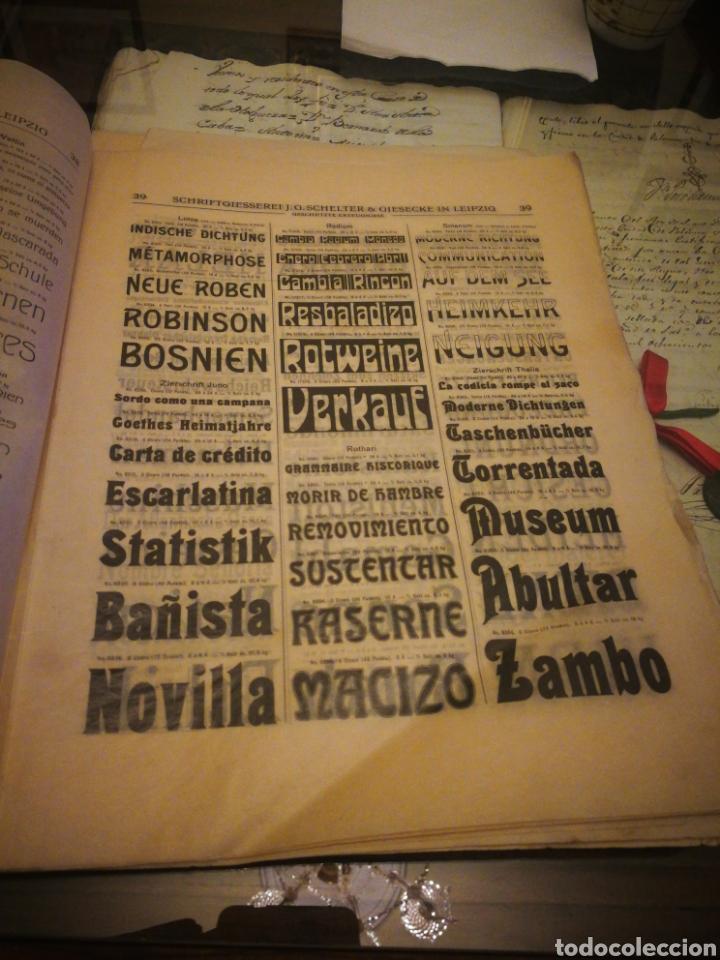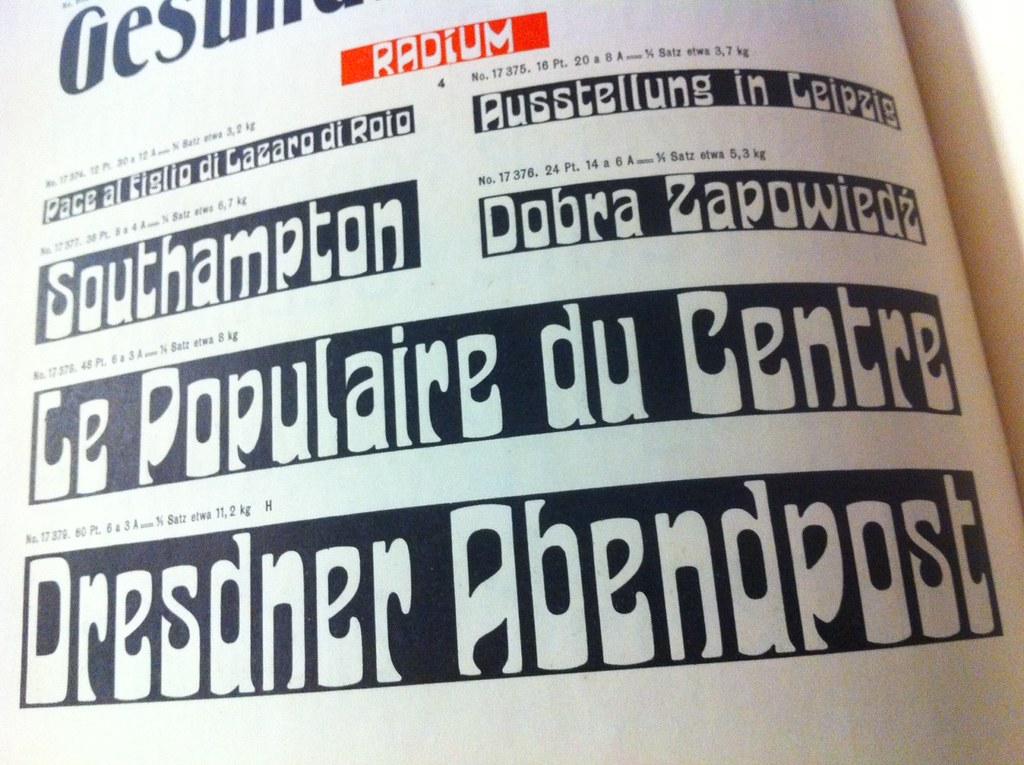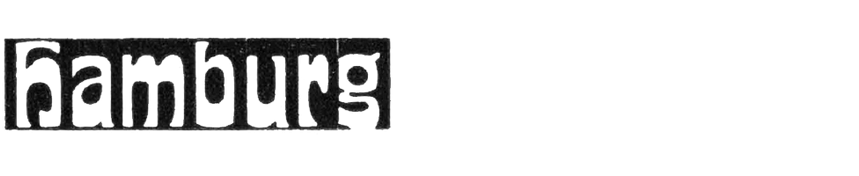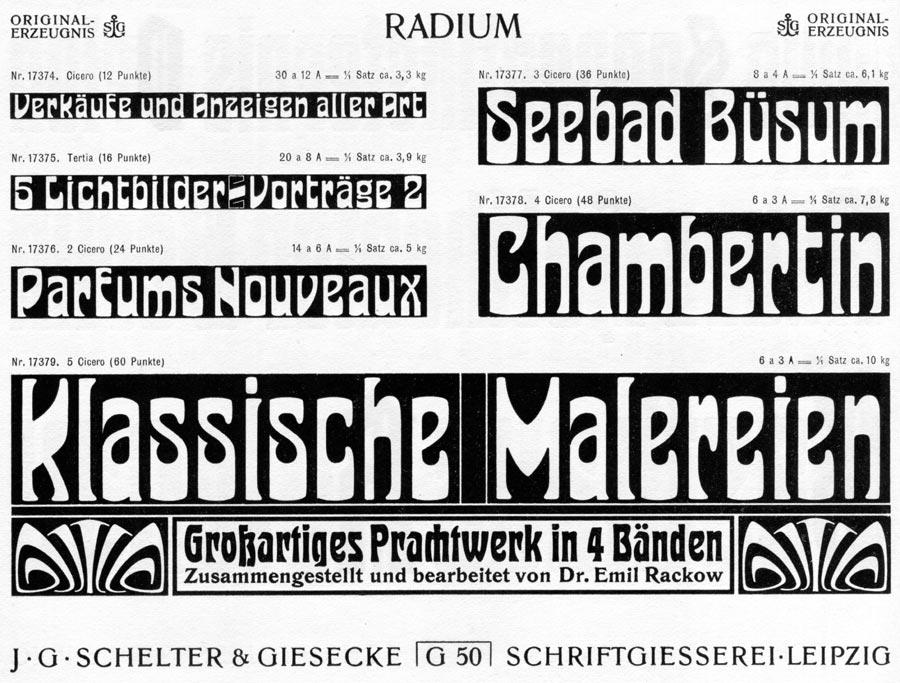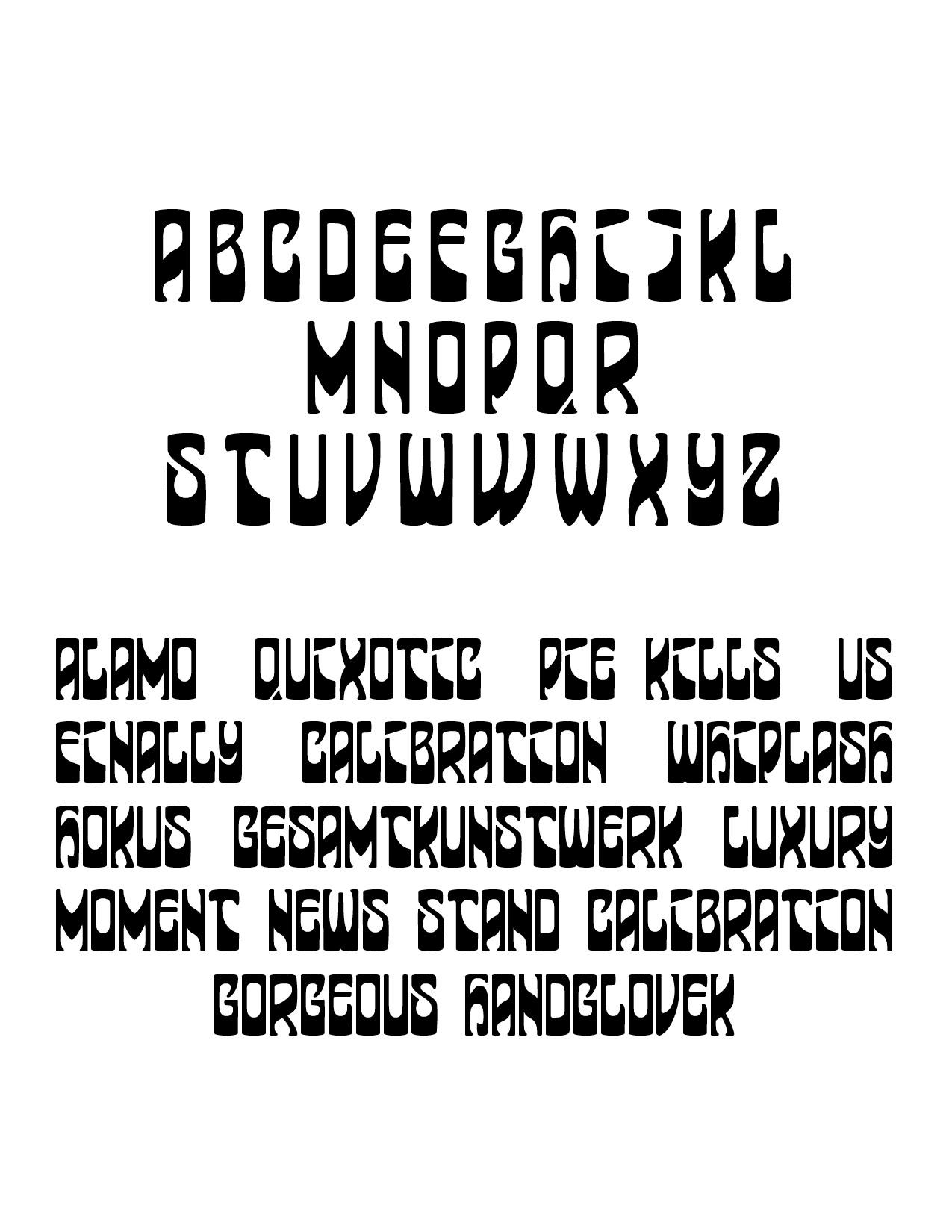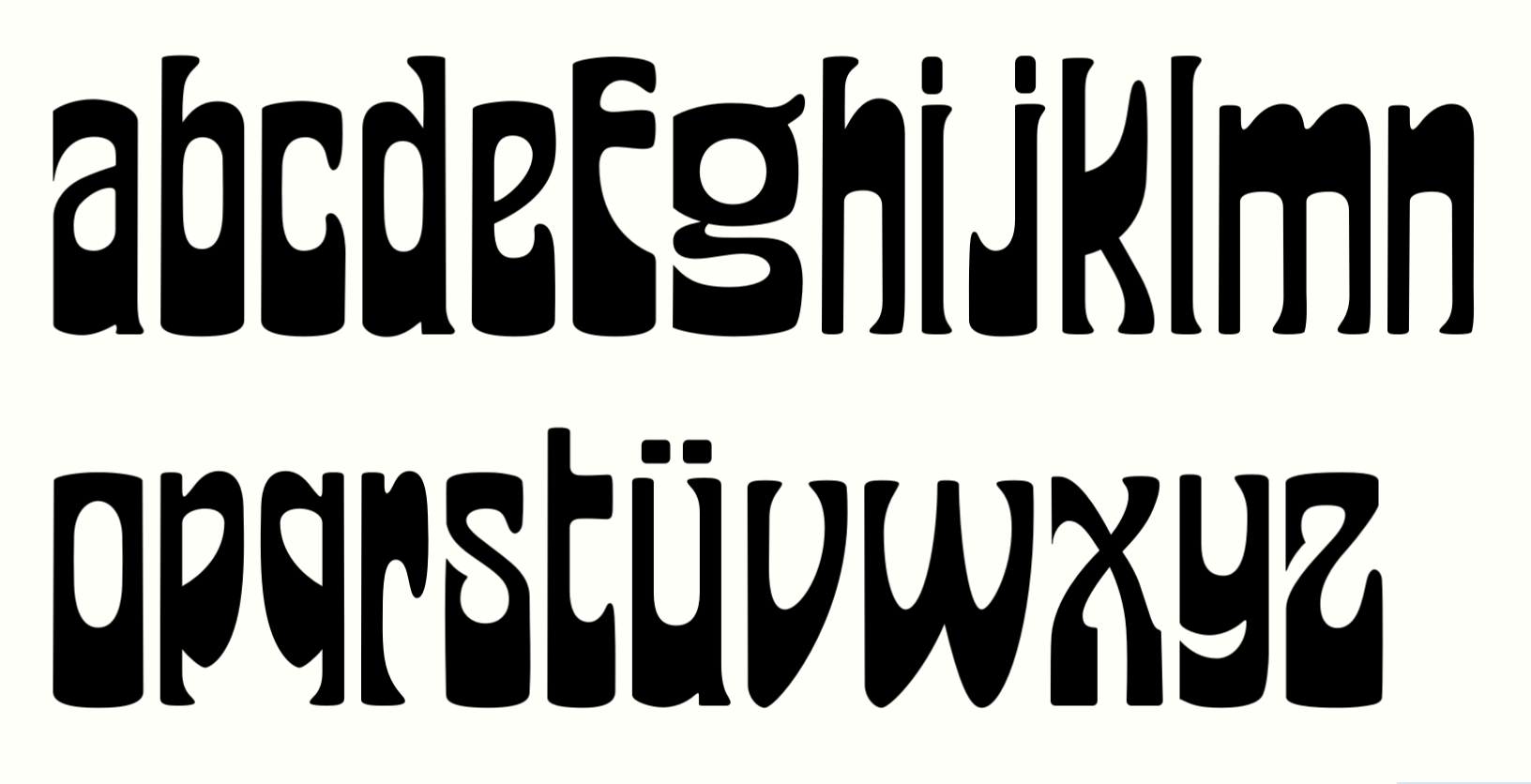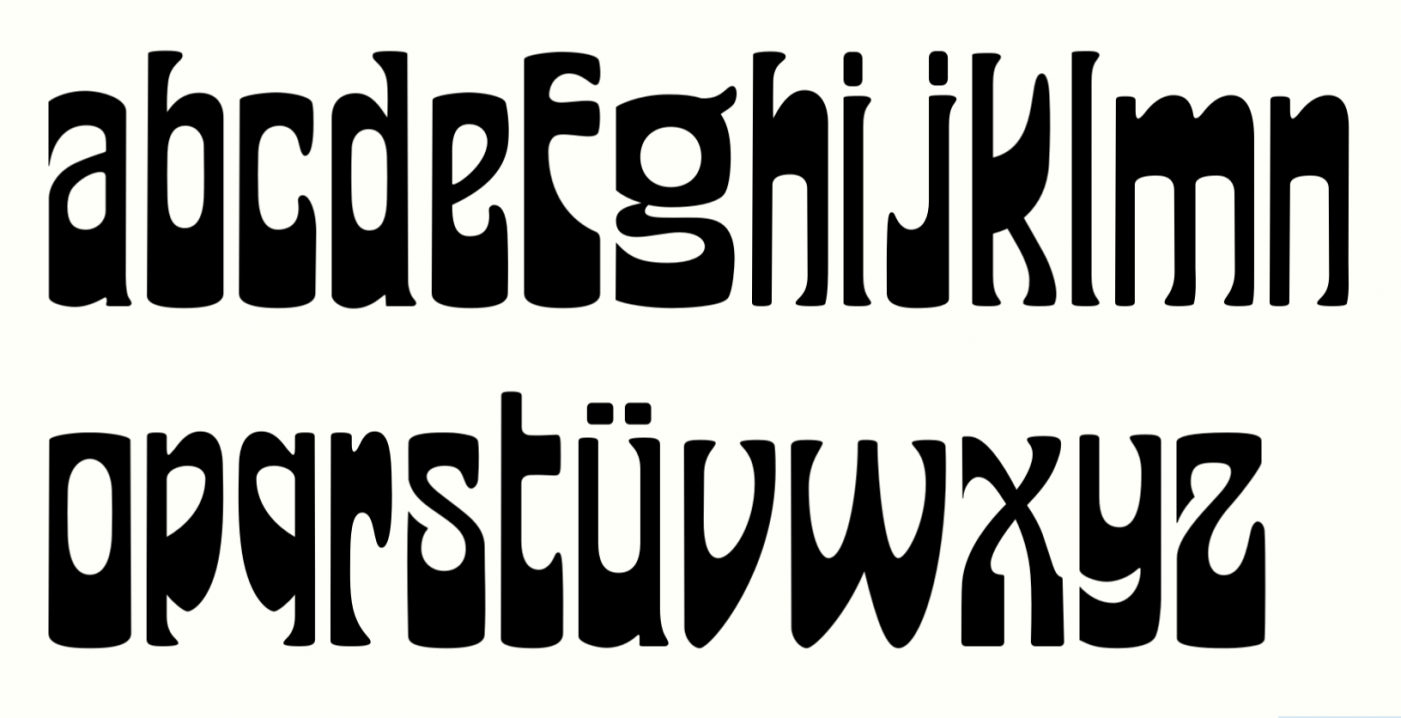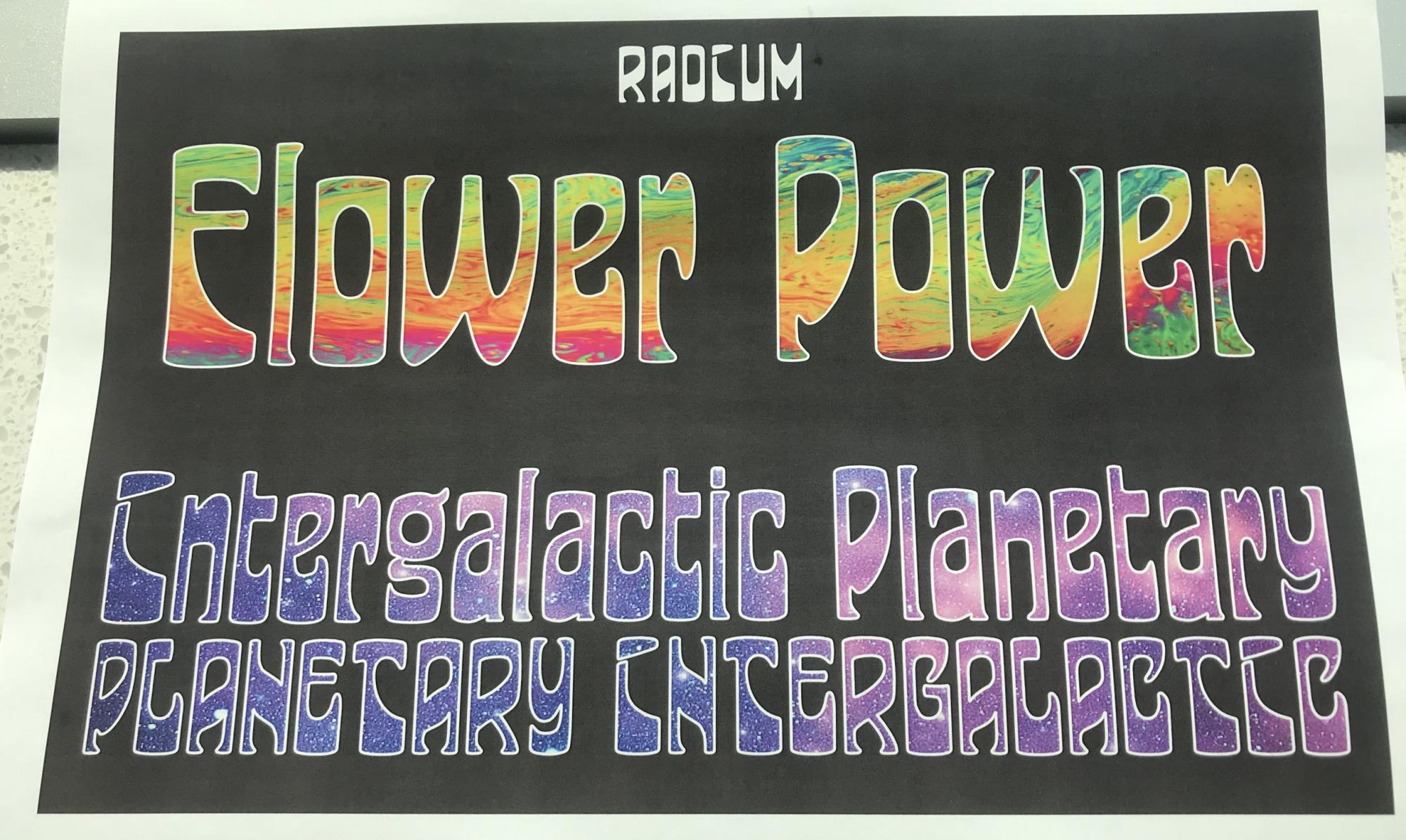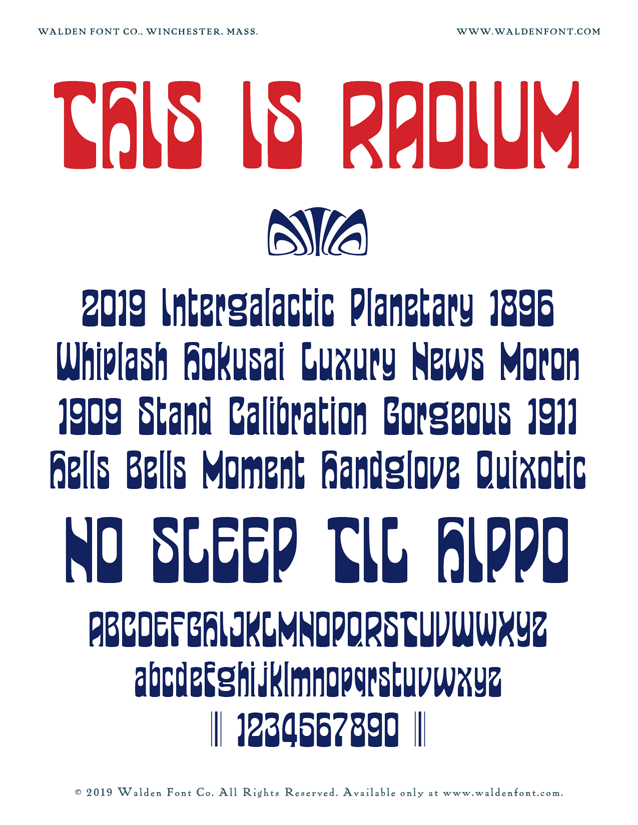
Suche Proben oder Anwendungsbeispiele der Radium von Schelter & Giesecke?
Ich murkse weiter am Jugendstil rum und suche jetzt nach Material zur Radium von Schelter & Giesecke (nicht mit der Radium von Ludwig Meyer zu verwechseln).
In meiner Hauptprobe von 1912 findet sich das angehängte, leider recht magere Beispiel. Das System ist daraus zwar ersichtlich, aber ich müßte doch arg viel frei dazu erfinden. Hat da jemand weiteres Material? Selbst einzelne Buchstaben würden mir schon helfen.
Bin beim googeln auf diesen Verriß gestoßen. Vielleicht sollte ich mir das mit der Radium nochmal gut überlegen :lol:
(aus dem "Archiv für Buchgewerbe und Gebrauchsgraphik", Band 42, 1906)
Vielen Dank, Bertel! Das erste und das dritte Bild habe ich auch gefunden, leider ohne Quellenangabe, aber das mittlere war mir unbekannt 🙂
Erste Gehversuche. Frei erfunden habe ich E, G, J, O, Q, T, W, X, Y. Für die anderen habe ich die obigen Vorlagen benutzt.
Noch ist nichts auf die richtige Breite abgestimmt, Maße abgeglichen, usw.
• F irritiert mich ungemein, weil es wie E aussieht. Ist aber in der Vorlage so. E kenne ich nicht, kann mir aber nicht vorstellen, daß es viel anders ist.
• Beim W kann ich mich beim besten Willen nicht für eine Form entscheiden, obwohl die erste es wohl nicht bringt.
• X - naja, ulkig ist es jedenfalls.
• Y? vielleicht zu schwarz geraten.
Übrigens kann Leserlichkeit hier gewiß nicht das Ziel gewesen sein 🙂
Sagt mir mal, was Ihr davon haltet!
Nachtrag: Gerade erspähten meine entzündeten Äuglein im mittleren der von Bertel eingestellten Bildern ein E. Das übersehen zu haben ist mir als altgedientem Fossiliensammler regelrecht peinlich!
Helfen tut es aber nicht: E und F sind sich auch hier sehr ähnlich. Der brutale Kritiker wird mir immer sympatischer.
Stimmt, auf beste Lesbarkeit ist die wahrlich nicht getrimmt, das kann aber durchaus auch Absicht sein,denn wenn ich überlege, welche Anschriften mit immer länger im Gedächtnis bleiben, sind es oft gerade die, an denen es etwas zu rätseln gibt, und man die nicht schon mit dem ersten Blick gelesen, und damit als unwichtig abgehandelt hat, noch befor man lange genug hingesehen hat, um dies im Gedächtnis zu behalten.
Doch jetzt zu meinen Gefühlen bei den Buchstaben:
1. Das E vs. F Problem ist wirklich doof. Vielleicht ja statt des viel zu E-igen F lieber ein F aus dem T bauen?
2. I und J könnten meines erachtens deutlich schmaler werden.
3. Auch das R müsste etwas schmaler werden, damit die Punze nicht breiter als bei A, O, P usw. ist.
4. X ist zwar ulkig, aber das ist ja letztlich die ganze Schrift, ich finde, es passt.
5. Y - ja, etwas dunkel, spiegele mal ein H vertikal.
6 W - da finde ich das erste passend, könnte jedoch gut retwas breiter werden
Danke Dir für Deine Rat, Peter. Ich werde das alles mal verdauen. Ich hoffe auch die Leserlichkeit wird besser wenn die Kleinbuchstaben dazu gekommen sind.
So, hier haben wir Kleinbuchstaben 1.0. Die sind aus verschiedenen Schnitten zusammengeklaubt, bzw. erahnt. Ich muß also die Maße abgleichen und alles auf eine harmonische Reihe bringen - nur nicht zu harmonisch, denn die Wirkung soll ja etwas skurril bleiben.
Ein etwaiges Problem: die Radium war als Negativschrift gezeichnet, so haben alle Zeichen links keine Weite ("side bearing" - wie deutscht sich das?), und sind offen. Daher die abrupten Senkrechten, besonders bei a und g. Warum das in der Bleischrift Sinn machte weiß ich nicht, sehe aber keinen Grund, es beizubehalten. Was meint Ihr?
Im Zweifel, Guru fragen: https://typography.guru/term/left-sidebearing-r70/
Ja, das sieht gar nicht gut aus.
Ich lese immer „Elower“... Hat es einen Grund, dass das „P“ unten rechts Luft haben darf, das „F“ aber nicht?
Genau das spukt mir schon von Anfang an im Kopf herum. :gimmifive:
F, I und i sind m.E. einfach zu komisch, um die Schrift auch nur halbwegs sinnvoll einsetzen zu können (wenn diese Buchstaben vorkommen). So toll Schrägheit sein kann, ein Minimum an Lesbarkeit muss schon sein.
Tja, hier kommt der Rat zur Anwendung, den Matthew Carter mir bezüglich meiner Wiederbelebungsversuche gegeben hat: “Revival isn’t taxidermy”. Ich werde mich also von der Vorgabe gezielt entfernen müssen, um ein brauchbares F zu erhalten. Bei I und J habe ich noch nicht ganz aufgegeben, da kann man vielleicht noch was machen. Alles in allem eine recht frustrierende Schrift. :neenee:
Verschiedene Vieren:
Mir gefällt die zweite 4, Elvis-4 :-)
Je größer die Tolle, desto toller ;-)
Würde mich interessieren! :-)
Ist dann aber halt ein recht extrovertierter Einzelgänger innerhalb von Ziffernreihen.